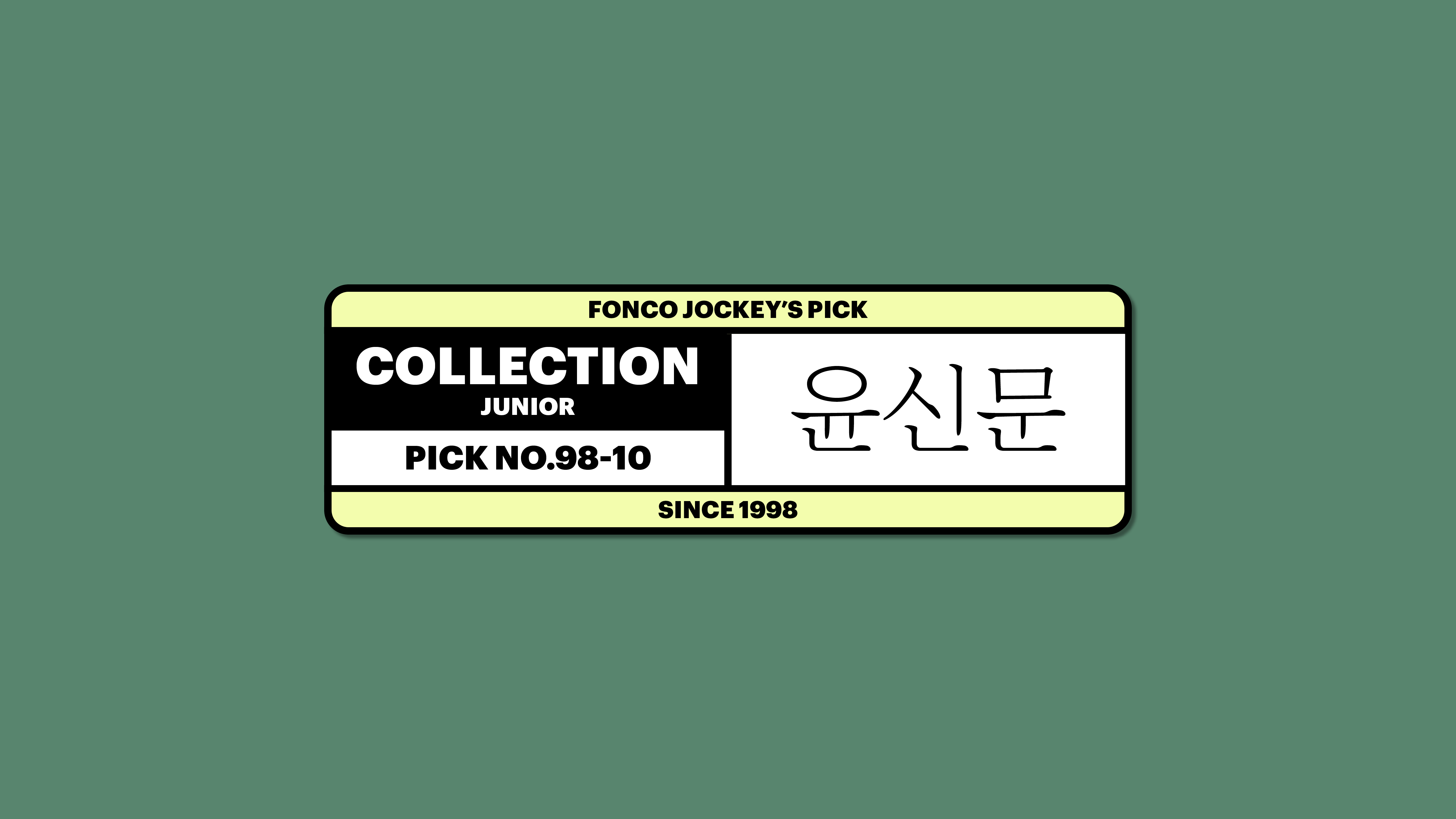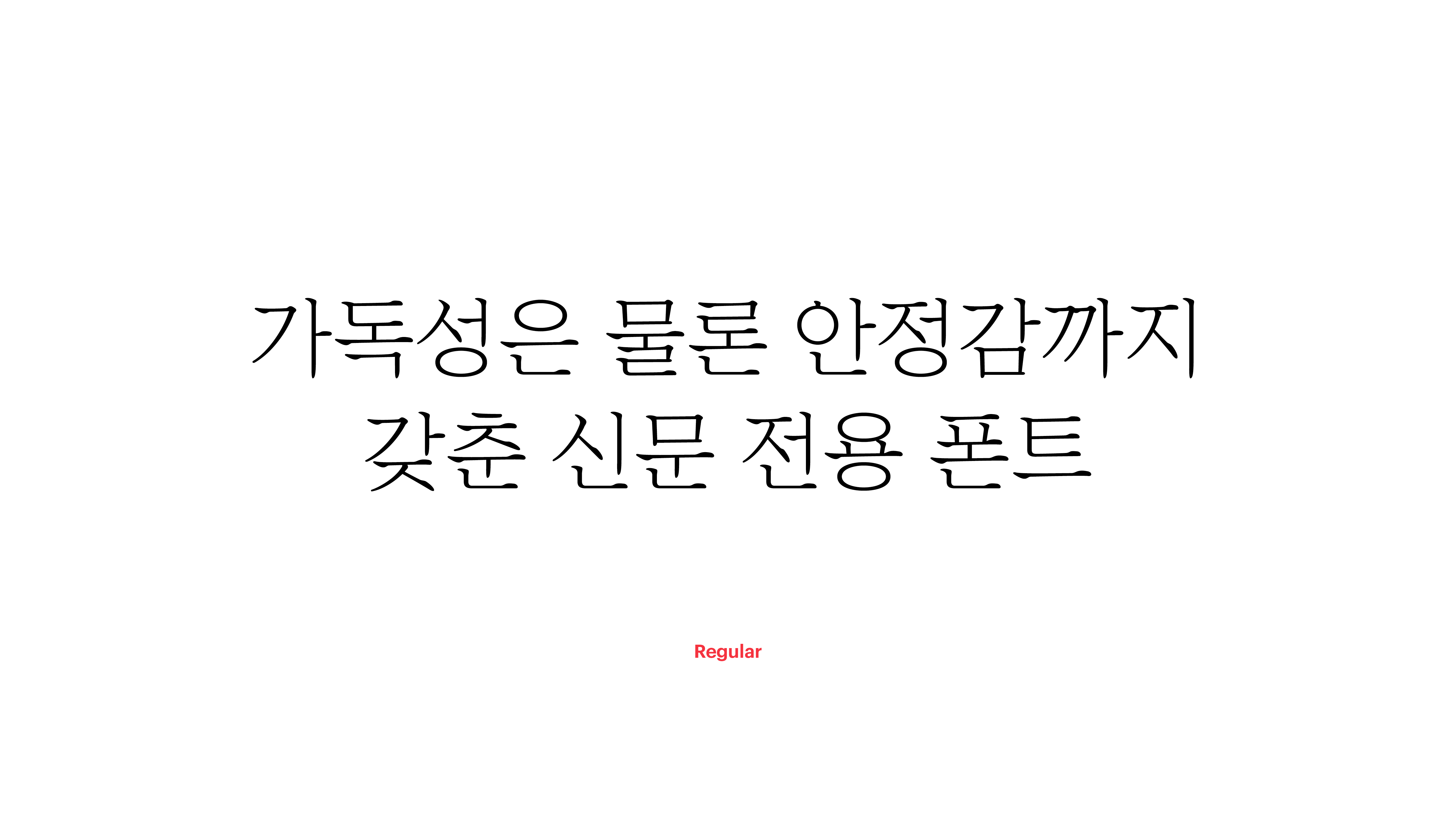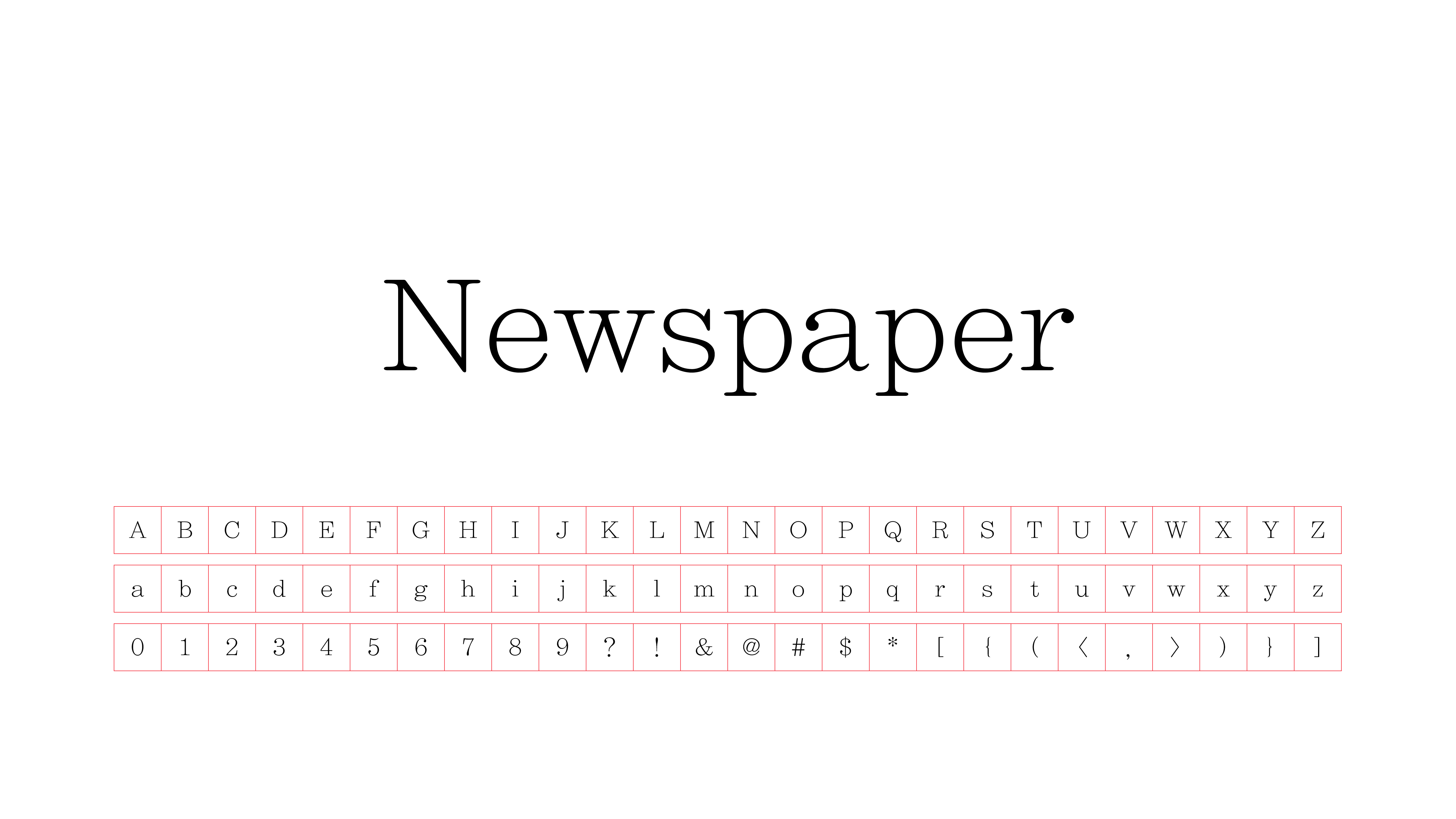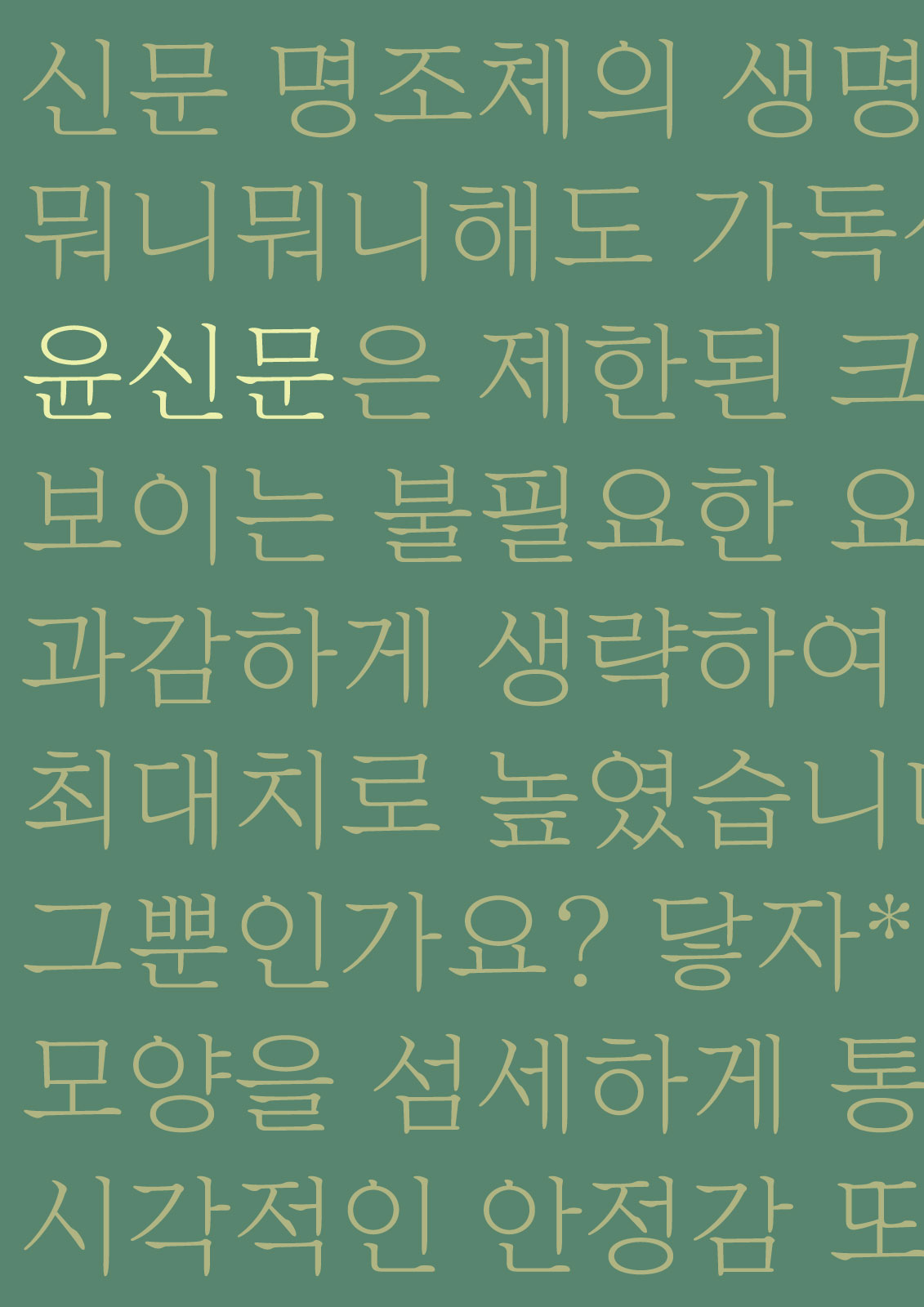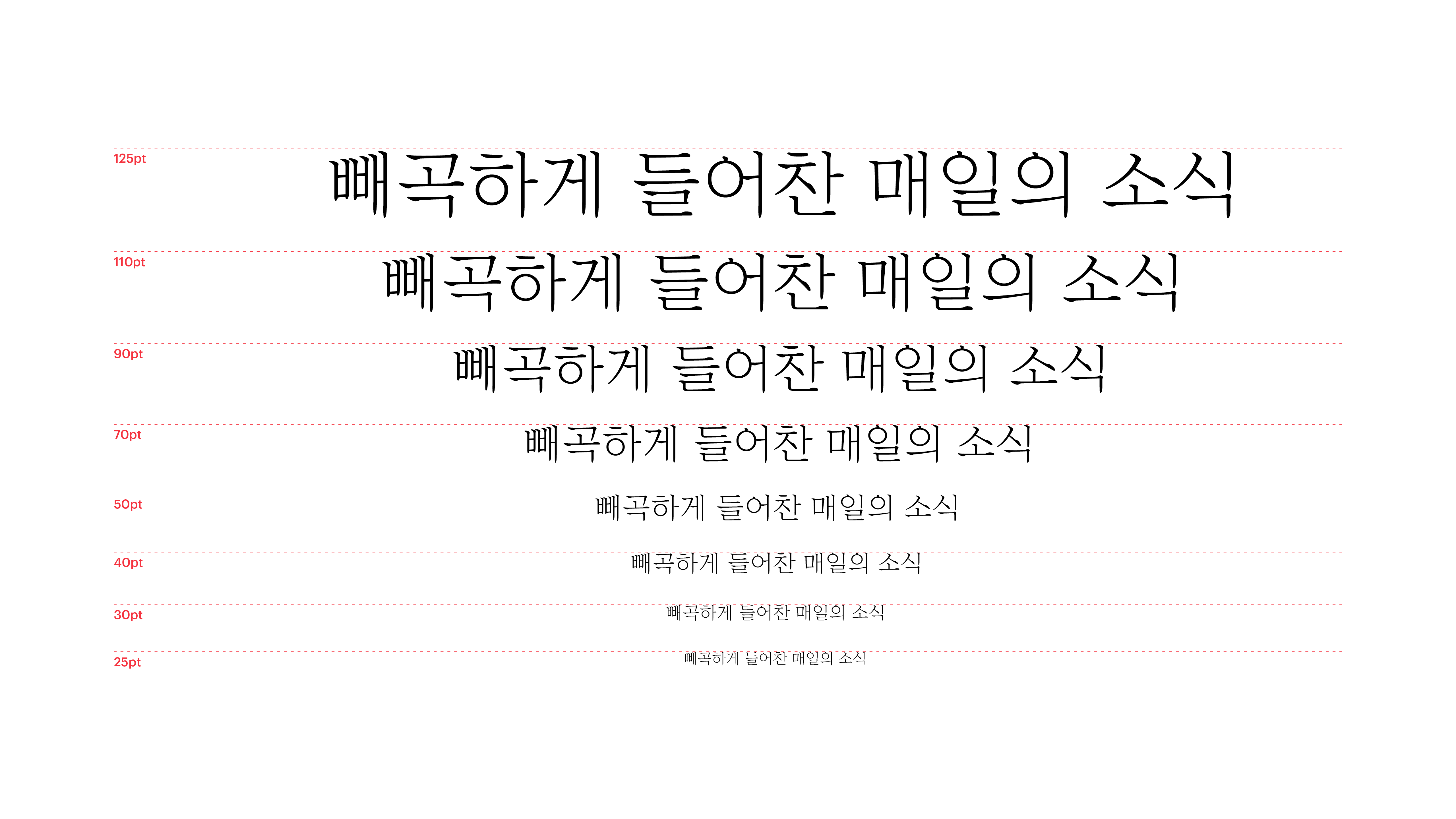
Yoon 윤신문
신문 명조체의 생명은 뭐니뭐니해도 가독성! 윤신문은 제한된 크기에서 보이는 불필요한 요소들을 과감하게 생략하여 가독성을 최대치로 높였습니다. 그뿐인가요? 닿자*의 크기와 모양을 섬세하게 통일하여 시각적인 안정감 또한 확보하였답니다. 빼곡하게 들어찬 매일의 소식, 윤신문체가 신속, 정확하게 전달하겠습니다. *닿자 : 한글 ‘닿소리 글자’의 줄임말, 자음을 시각적으로 일컫는 표현.